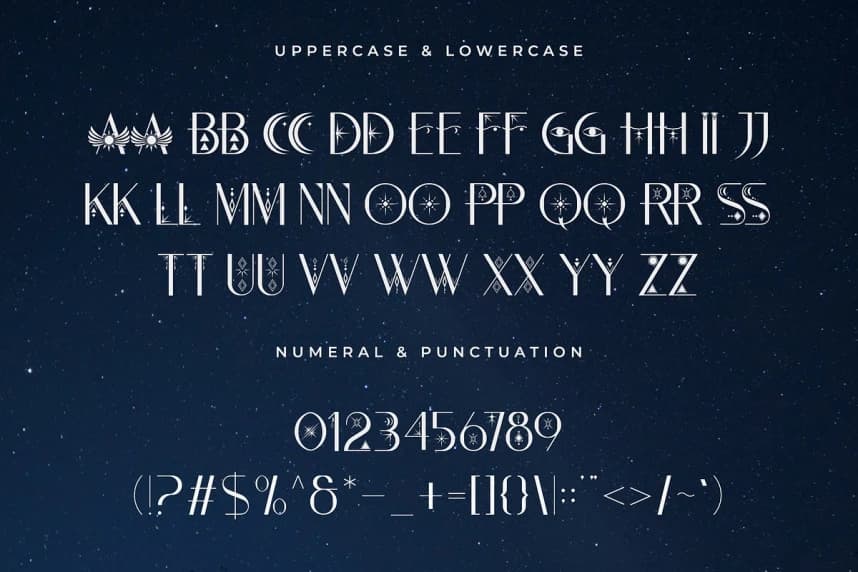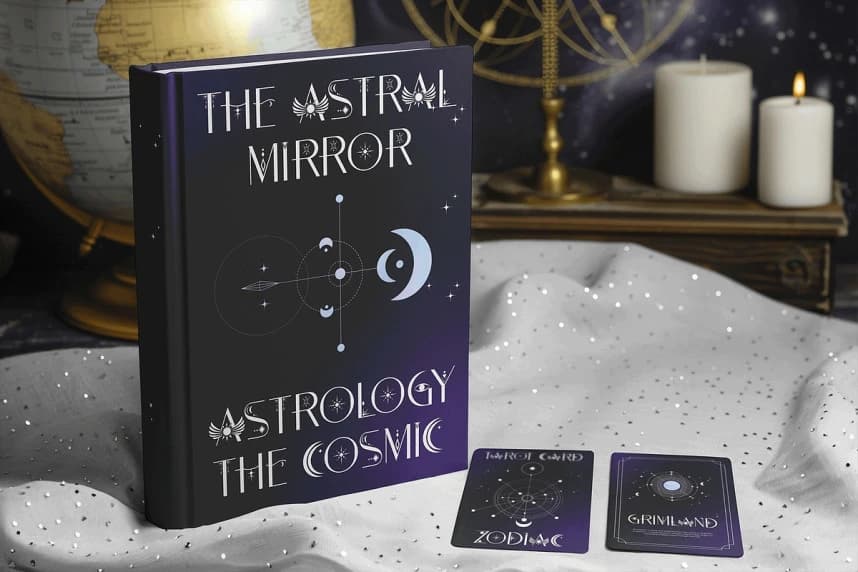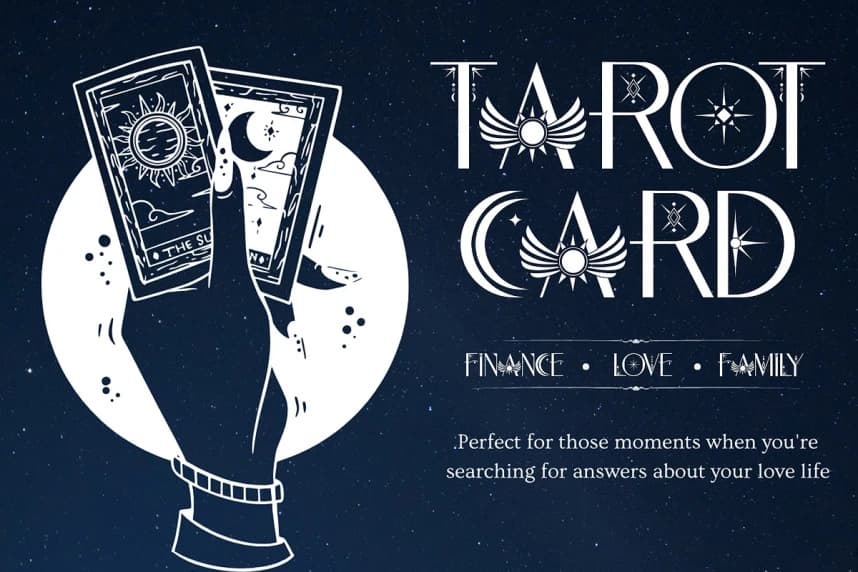
Umbratha Yazı Tipi
Umbratha Font, dikkat çekmek için tasarlanmış modern bir gösteri yazı tipidir; cesur biçimleri ve çarpıcı karakter tasarımıyla öne çıkar. Keskin kenarlara ve çağdaş bir havaya sahip olan Umbratha, başlıklar, posterler, marka oluşturma ve dijital sanat için mükemmel olan güçlü bir görsel etki sunar.
Umbratha Font, dikkat çekmek için tasarlanmış, kalın şekiller ve çarpıcı karakter tasarımıyla modern bir display yazı tipidir. Keskin kenarlara ve çağdaş bir hava katan Umbratha, başlıklar, afişler, marka kimliği ve dijital sanat için mükemmel olan güçlü bir görsel varlık sunar.